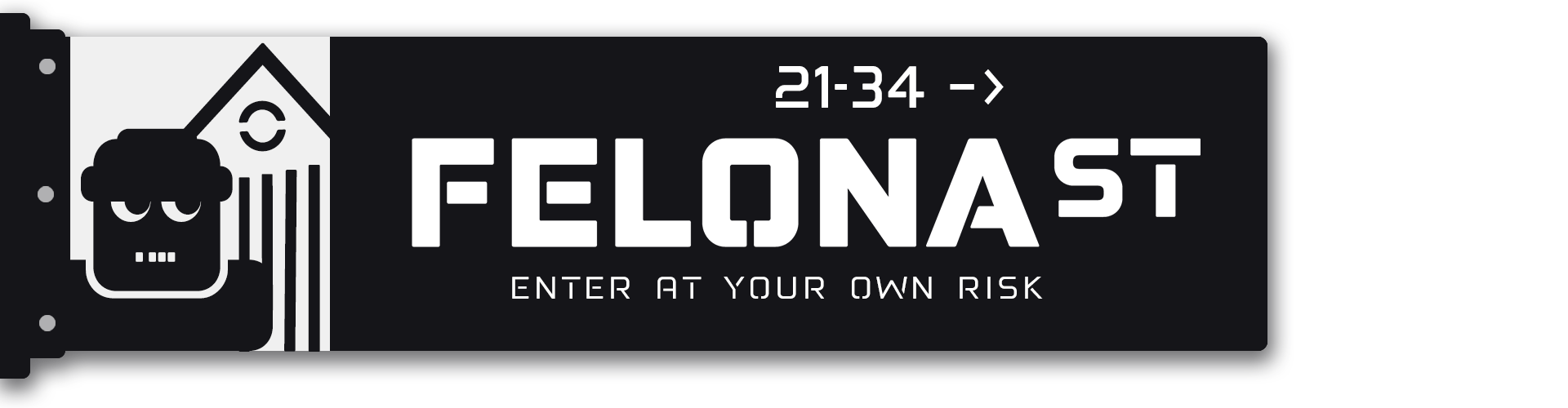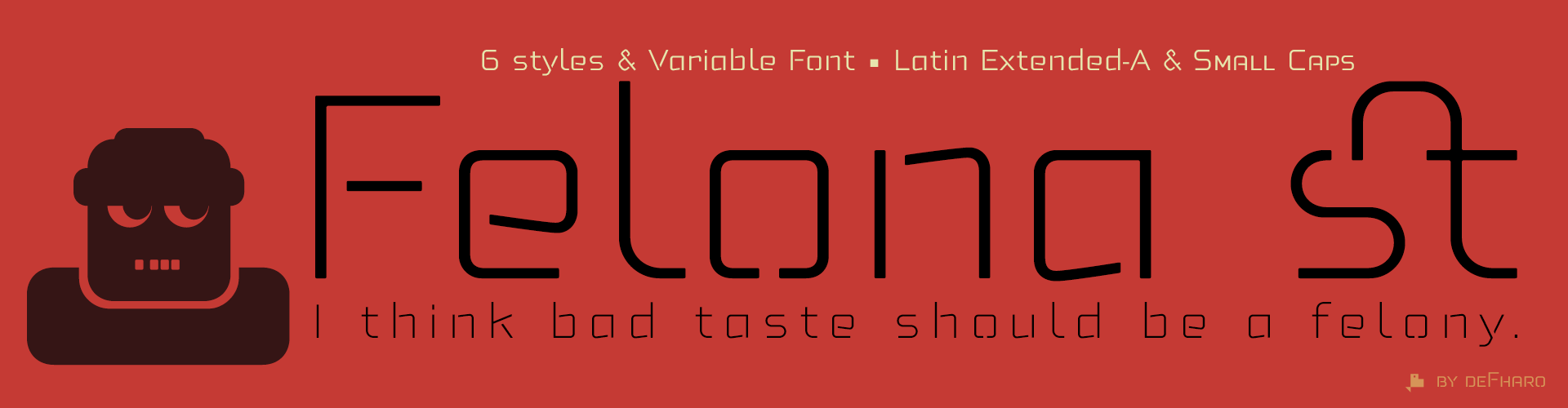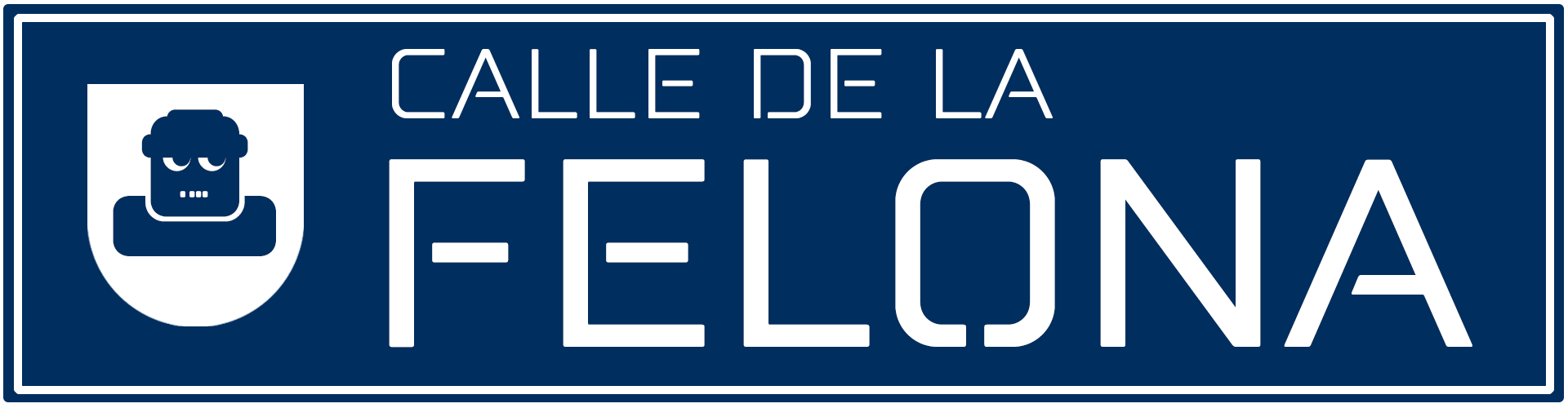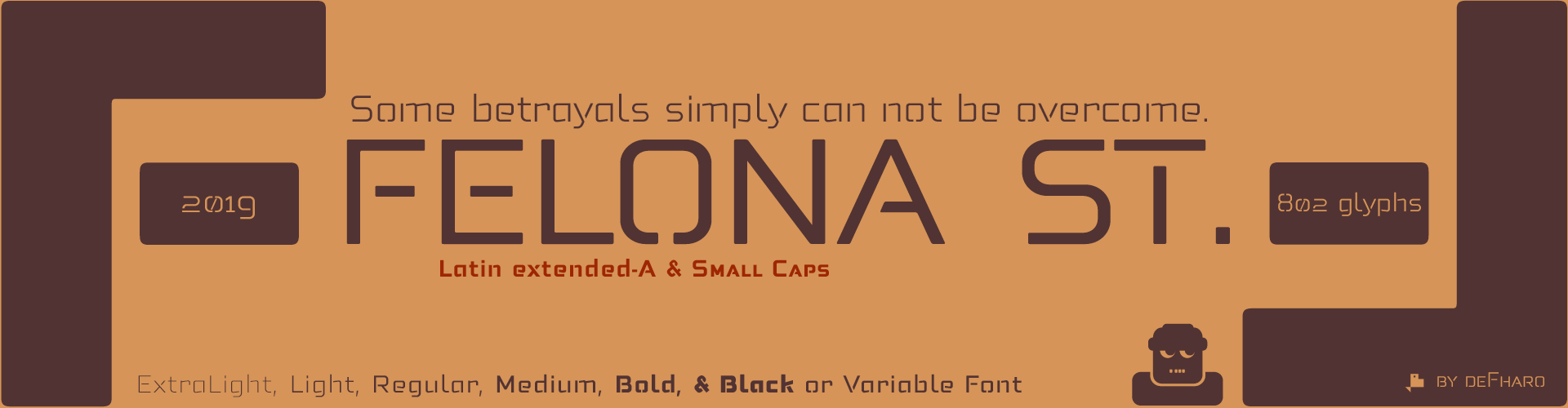
Neo Stencil 2019
Estilo: Sans Serif, Stencil, Techno, Small Caps
Proporción: Extra Light, Light, Regular, Medium, Bold & Black + Small Caps
Funciones OpenType: Additional languages, All Alternates, Alternate Annotation Forms, Bitcoin, Capital Spacing, Contextual Alternates, Denominators, Discretionary Ligatures, Extended Fractions, Historical Forms, Inferiors, Kerning, Localized Forms, Numerators, Oldstyle Figures, Ordinals, Scientific Inferiors, Slashed Zero, Small Capitals, Small Capitals From Capitals, Standard Ligatures, Stylistic Set, Subscript, Superior letters, Superiors, Superscript.
Felona st se enmarca en las tipografías de estilo tecnológico con formas redondeadas de hechura minimalista, en el caso de Felona la proporción de los cortes para convertirla en una fuente del tipo plantilla han sido muy cuidados, evitando cortes superfluos y creando otros originales. Ofrezco también 3 juegos alternativos de la letra A en mayúsculas, minúsculas y versalita. La legibilidad de esta tipografía está garantizada para cualquier tamaño y situación, tanto en imprenta o pantalla. Su uso en diseño gráfico, editorial y publicidad garantiza originalidad y diferencia. Unas fuentes muy versátiles para carteles publicitarios, vídeo juegos, títulos de cine, logotipos, publicaciones, etc. Incluye el símbolo del Bitcoin y otras cripto monedas.